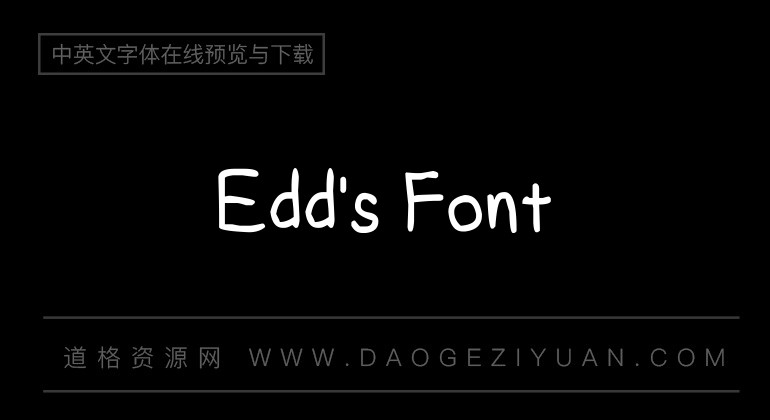
Edd's Font 是一款由英国设计师Edd Harrington创作的比较特别的字体,它的特点是字体的笔画比较粗糙,形状也比较不规则,非常有创意。它的颜色也比较深沉,给人一种很有冲击力的感觉。由于它的独特的设计,Edd's Font 字体可以用于很多不同的场景,比如海报、标志、广告等等。内容介绍
Edd's Font是一款非常不错的手写艺术字体,具有很好的视觉感,适合于文化类的宣传设计、商业类品牌的广告和产品包装设计以及个性化文字排版等较多场景。